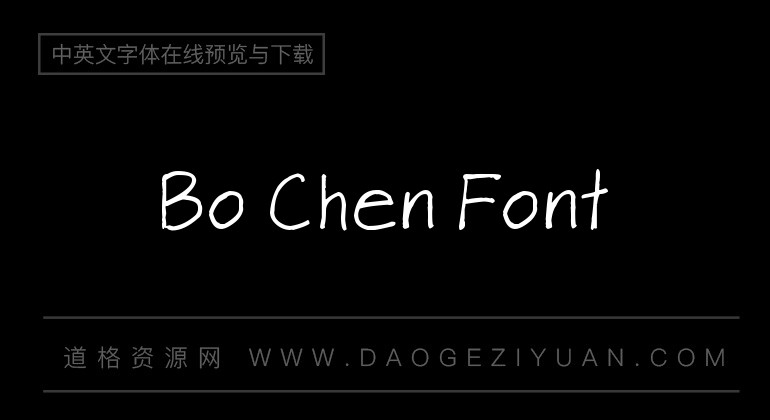
Bo Chen Font
Bo Chen Font 是由深圳设计师Bo Chen设计的一款时尚、清新、可爱的英文字体,特别适合用于商业广告、海报、文案、品牌形象等场景,具有良好的可读性和美观性。Bo Chen Font 字体拥有清新明快的风格,简约大方,搭配淡雅的色调,展现出清新的时尚感。字体的笔画宽度较细,给人以轻松、清新的感觉,搭配合适的背景,能够体现出活力与清新的气息。
Bo Chen Font是一款非常不错的手写艺术字体,具有很好的视觉感,适合于文化类的宣传设计、商业类品牌的广告和产品包装设计以及个性化文字排版等较多场景。